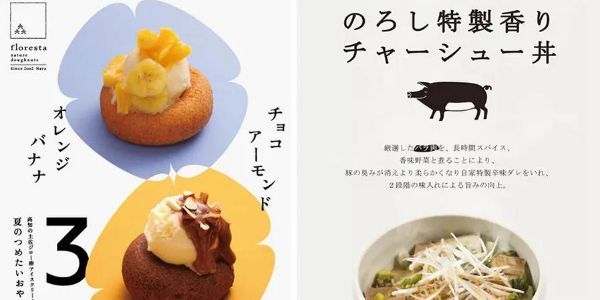
字体设计的最新玩法分享
它来了,它来了,蒙纳(Monotype)工作室发布的《2021年字体设计与应用趋势报告》终于来了。
在今年的报告里,蒙纳工作室的字体创意总监、字体设计师Charles Nix和字体公司Fontsmith的创意总监、字体设计师Phil Garnham两位业界专业人士亲自下场,深入观察目前字体排印设计的新动向,总结出了12种趋势。不管你是想要了解技术进步是如何影响字体使用的设计师,还是想要了解品牌如何使用字体与消费者建立联系的品牌从业者,这份报告里介绍的新趋势,你一个都不想错过。
·可变速度·
(Variable Speed)
设计师们通过压缩或者拉伸,改变字母造型的形状。玩一场视觉上的时间游戏,造成延时或者快进的错觉。这样的字体设计风潮将会给设计界另一种可能。
上个世纪,利用改变字符的重量呈现出不同效果的设计思路曾风靡过一段时间。但不同的是,因为科技的提升,我们可以使用更便捷的方法创造出非凡的效果。
·虚拟即现实·
(Variable Reality)
VR和AR的发展越来越快速,而字体也在不断地发展,以适应这种全新的体验方式。蒙纳工作室在报告中指出:“字体可以结合建筑空间设计,根据参与者的位置和观看角度发生变化,与其产生互动。”
字体设计师们,是时候思考这个问题了:跳出平面的字体有多少种特殊的呈现方式?
·可触碰的字体·
(Touchable Type)
带有人文主义关怀的无衬线字体和圆润的几何无衬线字体正式复出,让我们看到了品牌温暖的一面。与犀利的带衬线字体相比,无衬线字体显得温柔,如果你所服务的品牌想走温暖人心的路线,是时候把衬线拿掉了。
·原力·
(The Force)
愿原力与你同在(May the force be with you),这句话是绝地武士之间的祝福。但在星球大战的logo设计里,我们却发现“R”的末笔不符常规,进行了延长处理。
蒙纳工作室在报告里指出,在最近的平面设计中,这样造型的R也多有出现,通过这一个字母的特殊设计就可以让品牌表达跳脱出来,何乐而不为呢?
·更多的软服务·
(More Soft-serve, Please)
什么是“软服务”?从蒙纳工作室看来,是通过使用1910年代和1920年代略带圆弧的字体,来表达品牌友善的态度。具有怀旧质感的衬线,能够拉近与客户之间的距离。
最好的范例,可以参照汉堡王品牌的实践。用圆润的字体,取代以前棱角分明的字体,汉堡王通过引发人们的怀旧情绪,让客户对品牌的好感倍增。
·手写仍在·
(Hand was Here)
虽然现在大部分设计工作都可以在电脑完成,各种各样的免费数码字体也能让设计师们放开束缚,各展所长。但蒙纳工作室的报告却指出,在完全数码化的环境中,我们寻求手作质感的人文与品质。
在科技的助力下,通过电脑我们也可以模仿出灵动的手写字体。跳脱出数码字体的规整,有时候稍微“出格”一点,就能让你的设计格外出众。
·奢华无衬线体 VS 慵懒衬线体·
并不矛盾,无衬线体和带衬线体同时加入了流行趋势。取决于你所在品牌想要展示出来的形象,衬线可以是你最好的朋友,也可以是你最坏的敌人。
如果你想采用无衬线字体,请注意你选择的字体需要带有笔画的粗细对比,这样能够让你的品牌形象更有质感。
而如果你想采用带有衬线的字体,记得要选那些带有连笔笔画的字体,这样会让你的品牌有着极强的风格化效果,并且颇具时尚感。如果你希望你的品牌轻松而充满活力,带有衬线字体,连带着那些曲线会帮你达到目的。
·侧方移动·
对字母的粗细线条进行简单的调整,你很快就能得到一个反传统的设计——或者说过于传统,所以看起来有些新奇的设计。毕竟,风潮来来去去。
在今日的数码时代,只需要在选择字体时注意粗细的对比使用,创造出一种风格鲜明的对比,就可以创造出更多充满实验性的设计作品,为品牌传达出不同的声音。
·砖块头·
不再是笨重的象征,这些宛如砖块头一般的字体反而流露出可爱的元素。将复古的指针稍微往前拨一点,在80年代稍作停留。用带有数码朋克风的大字号字体来表达对于往日情怀的怀念。
通过使用这种字体,可以有效地提高品牌的存在感,尤其是在创意和数码领域。想想看,当所有人在追逐未来或者回溯过往时,你的品牌用稍微有点怀旧的风格出镜,是不是一下就跳脱出来了?
·要点放大·
如果要让别人注意到你想表达的,放大也许是最便捷的途径。
超大的字体代表着你对品牌的自信,让更多的人见到你品牌的名字。在设计入门当中,我们就知道要将重要的信息放大处理,让更多的人能够更快地找到信息要点。在品牌宣传与推广上,这一点同样适用。在今年,遮遮掩掩不是主流,自信展示将大放光芒。
·量化的严苛·
设计无小事,特别是在字体上。一个字号的差别,很有可能会带来截然不同的感觉。
对于强迫症患者而言,今年是属于他们的一年。强调干净、易读、客观的国际主义设计风格回潮,用非对称排版、栅格、靠左对齐等特征席卷设计界。你喜欢一个像素接着一个像素排版吗?Well,大展拳脚的时候到了。
好了,这就是蒙纳工作室介绍的12种新趋势,你看好哪种趋势会在今年大行其道?